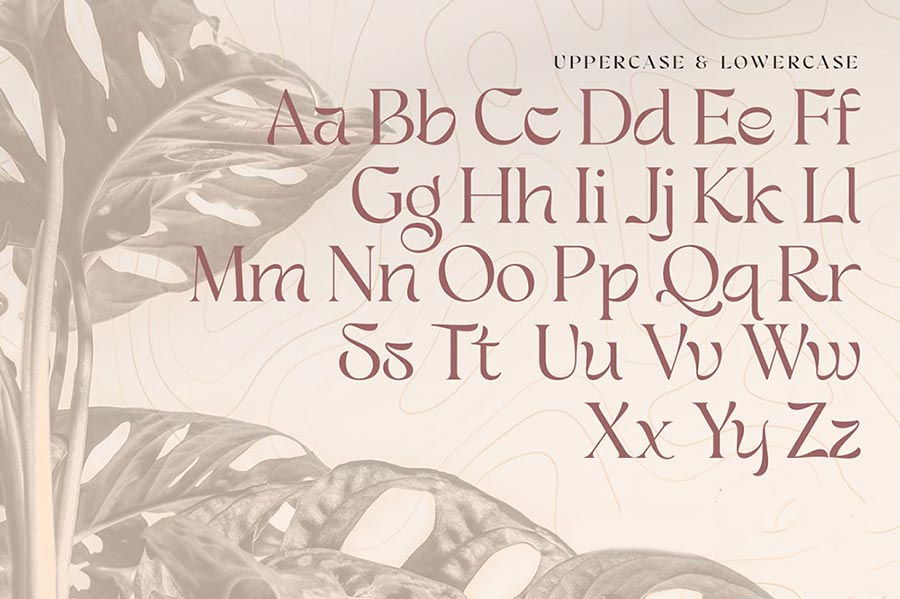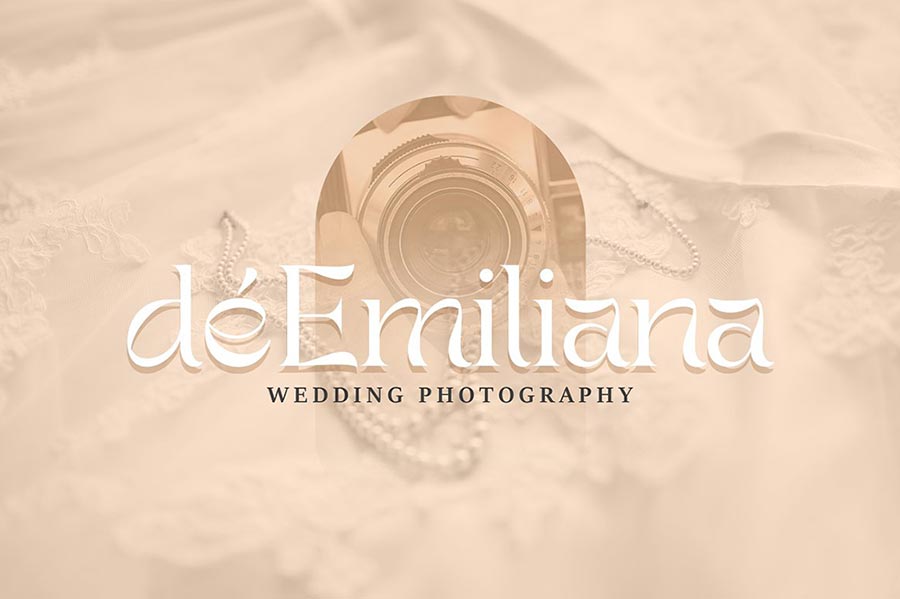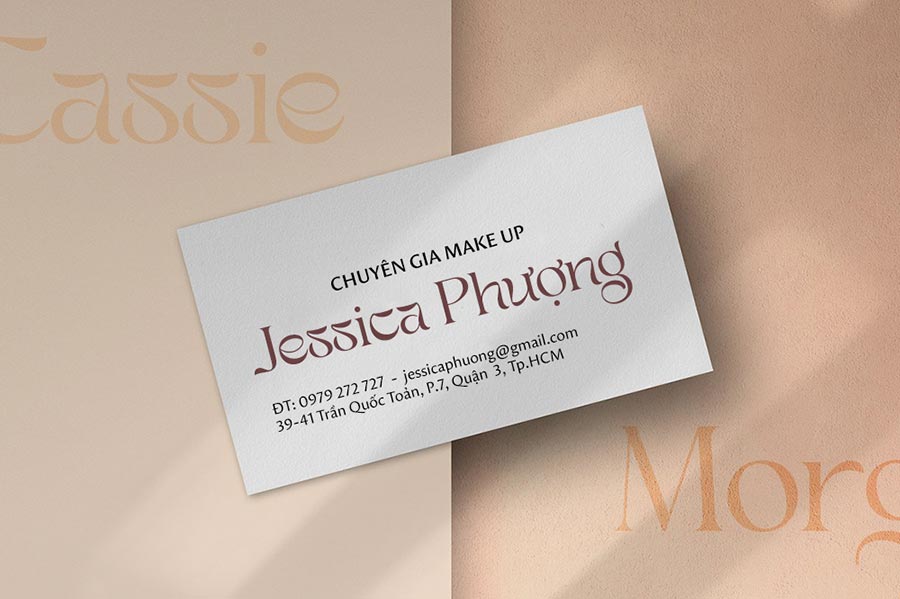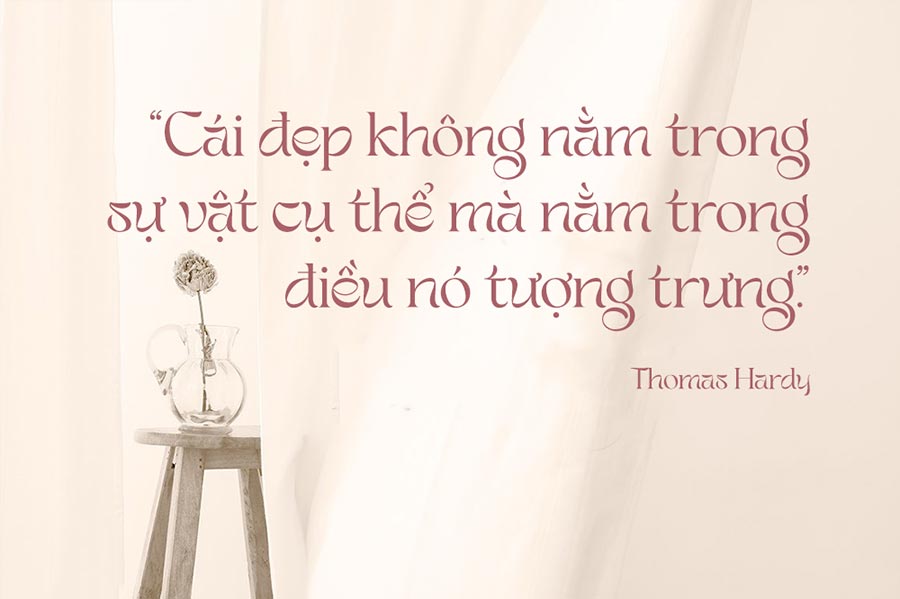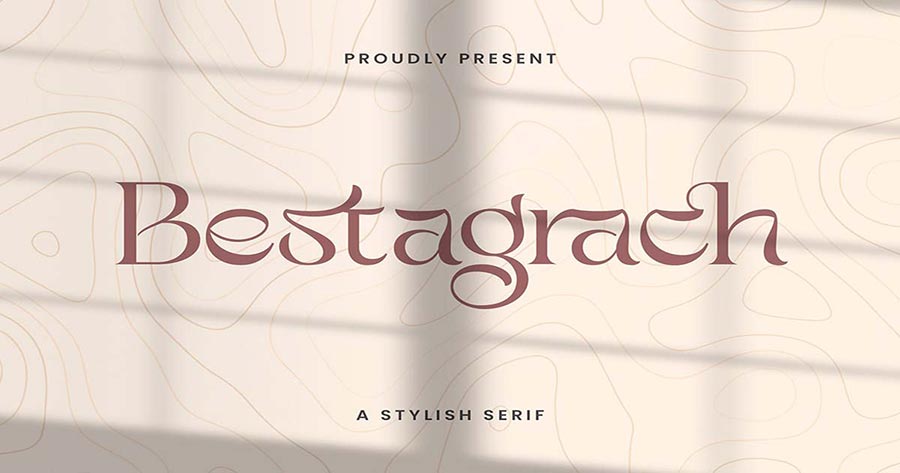
Chia Sẻ Miễn Phí Font Việt Hóa SVN-Bestagrach Chữ Nối Sáng Tạo
Trong lĩnh vực thiết kế đồ họa và truyền thông, font chữ đóng vai trò quan trọng trong việc truyền tải thông điệp và tạo dựng thương hiệu. Việc sử dụng font chữ phù hợp không chỉ giúp tăng tính thẩm mỹ mà còn thể hiện được cá tính và bản sắc của sản phẩm. Trong bối cảnh đó, font chữ Việt hóa SVN-Bestagrach nổi lên như một lựa chọn sáng tạo và miễn phí cho cộng đồng thiết kế.
Font SVN-Bestagrach là một trong những font chữ nổi bật với thiết kế chữ nối độc đáo, mang lại sự mềm mại và linh hoạt cho các sản phẩm thiết kế. Với sự hỗ trợ đầy đủ các ký tự tiếng Việt, font này giúp các nhà thiết kế dễ dàng ứng dụng vào các dự án cần sự sáng tạo và khác biệt.
Một trong những ưu điểm nổi bật của SVN-Bestagrach chính là khả năng thích ứng linh hoạt với nhiều phong cách thiết kế khác nhau, từ hiện đại đến cổ điển. Điều này giúp các nhà thiết kế có thể dễ dàng áp dụng font vào nhiều loại hình sản phẩm như poster, thiệp mời, logo, và các ấn phẩm quảng cáo khác.